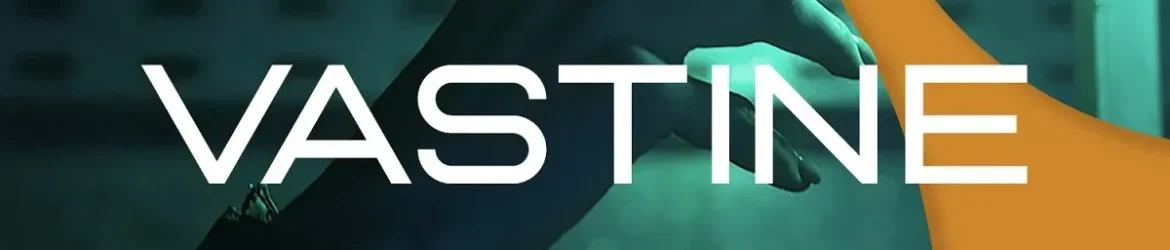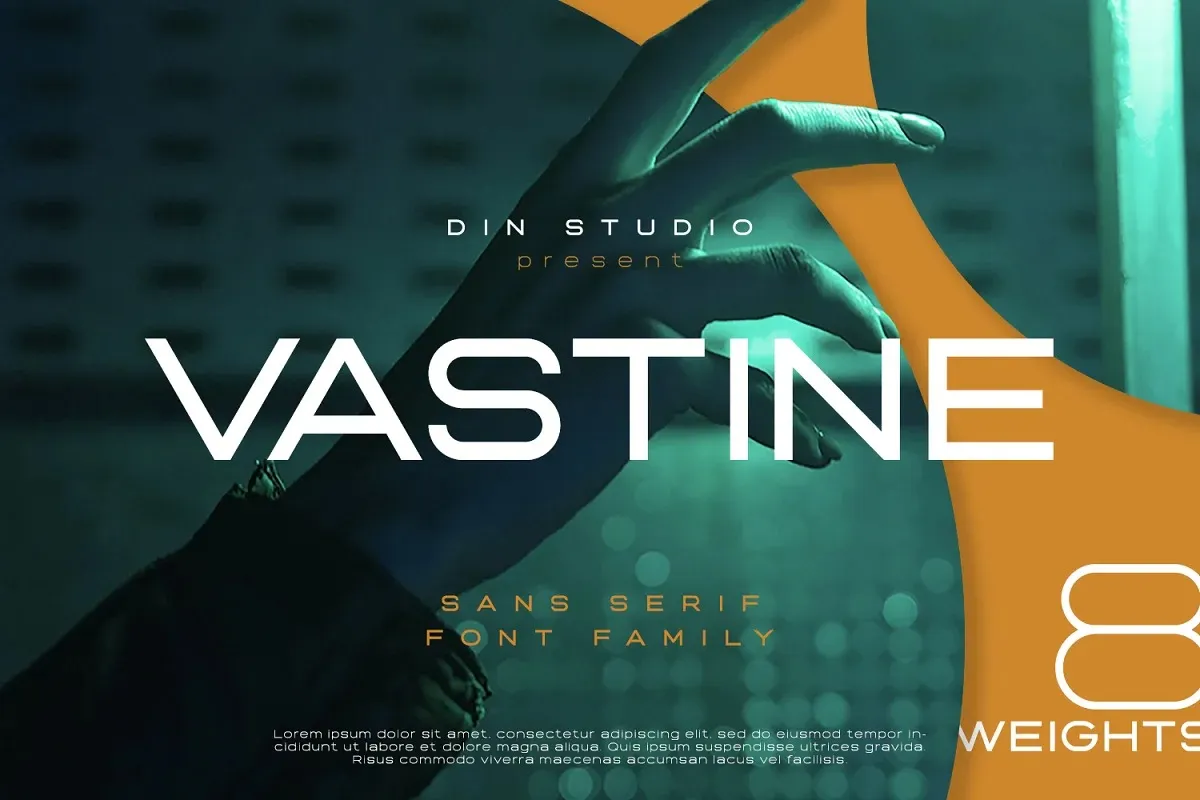
Vastine Font
A Vastine Font é uma elegante e moderna tipografia de sans-serif que traz sofisticação aos projetos de design. Com sua família de caracteres maiúsculas e minúsculas, a Vastine ajuda os designers a criar uma aparência agradável, ao mesmo tempo que é fácil de ler. Seu objetivo principal é tornar as marcas, logos, menus e ilustrações para redes sociais muito mais interessantes e modernas. É perfeita para criação de títulos chamativos ou design gráfico em geral. Combinando elegância com simplicidade, a Vastine se destaca como uma fonte que pode transformar seu projeto visualmente em algo inovador e sofisticado. E tudo isto sem necessariamente ter um estilo muito marcante, tornando-a adequada para diversos tipos de projetos.